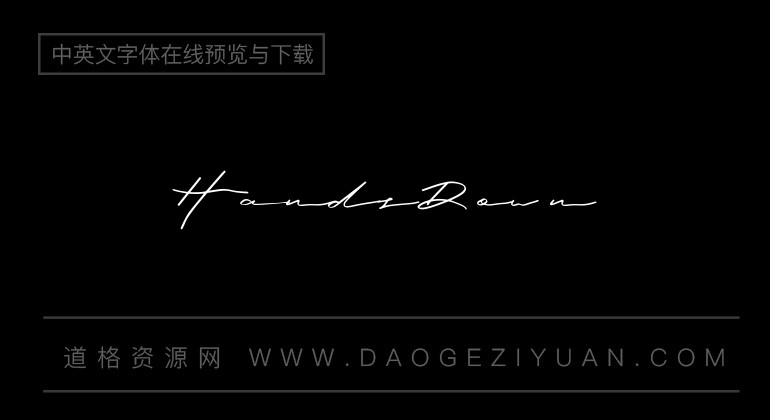
HandsDown 是一款简洁时尚的字体,由英国设计师Nina Geometrieva创作。这款字体简约大方,适用于大多数设计作品,比如广告、海报、宣传册等。它的特点是细节丰富,笔画流畅,拥有更多的可读性,能够在小字号下保持清晰,同时具有良好的可视性。它还拥有多种字重,用户可以根据自己的需求来调节字体的粗细度,从而使文字更加突出。内容介绍
HandsDown是一款非常不错的手写艺术字体,具有很好的视觉感,适合于文化类的宣传设计、商业类品牌的广告和产品包装设计以及个性化文字排版等较多场景。